今回は、Sofie Beier著、『Reading Letters』を紹介します。
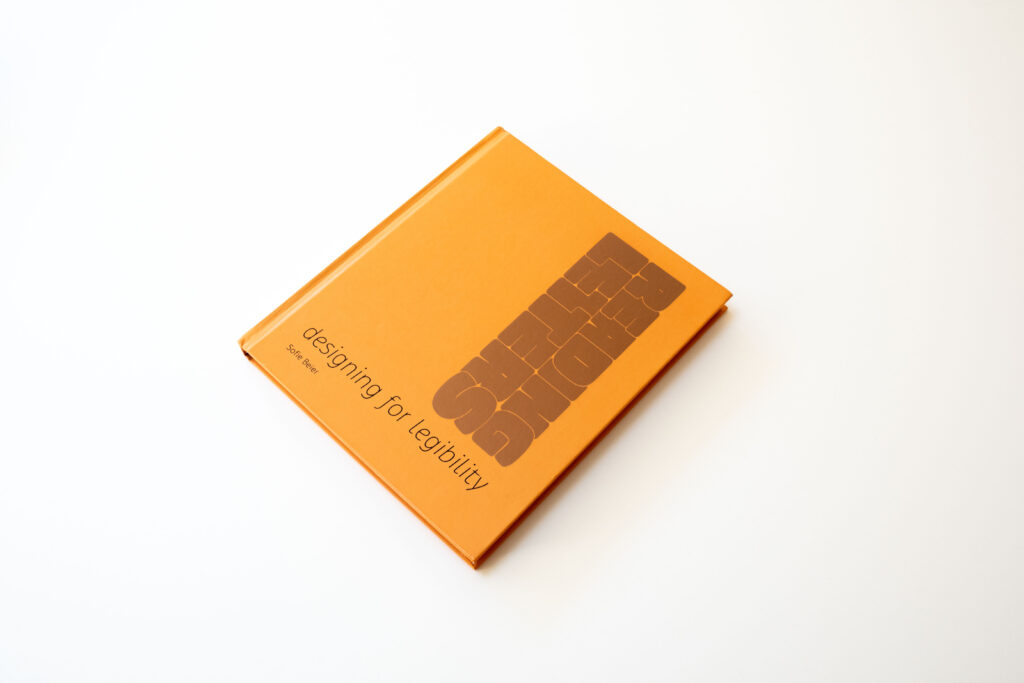
本書は書体の視認性ついて詳しく解説しています。一見硬いテーマですが、見るだけで納得がいく図版も豊富に取り入れている為、簡単に理解できるように工夫されています。また、視認性という大きなテーマはありつつ、文字の歴史、形状、視点移動や人と文字との距離などといった本当に様々な方面から掘り下げているため飽きることなく読み進めることができます。
書体において読みやすい、というのはどういうことなのか。簡単なように思えて、かなり深いテーマに歴代の書体デザイナー達がどのように向き合い書体を制作してきたか、またそれを筆者が根気よく考察していることが理解できます。それでもなお明確な答えはありません。しかし、様々な観点から考えることでその書体なりの最善に近づくことができると思わせてくれます。書体の視認性について深く学んでみたい方におすすめの一冊です。